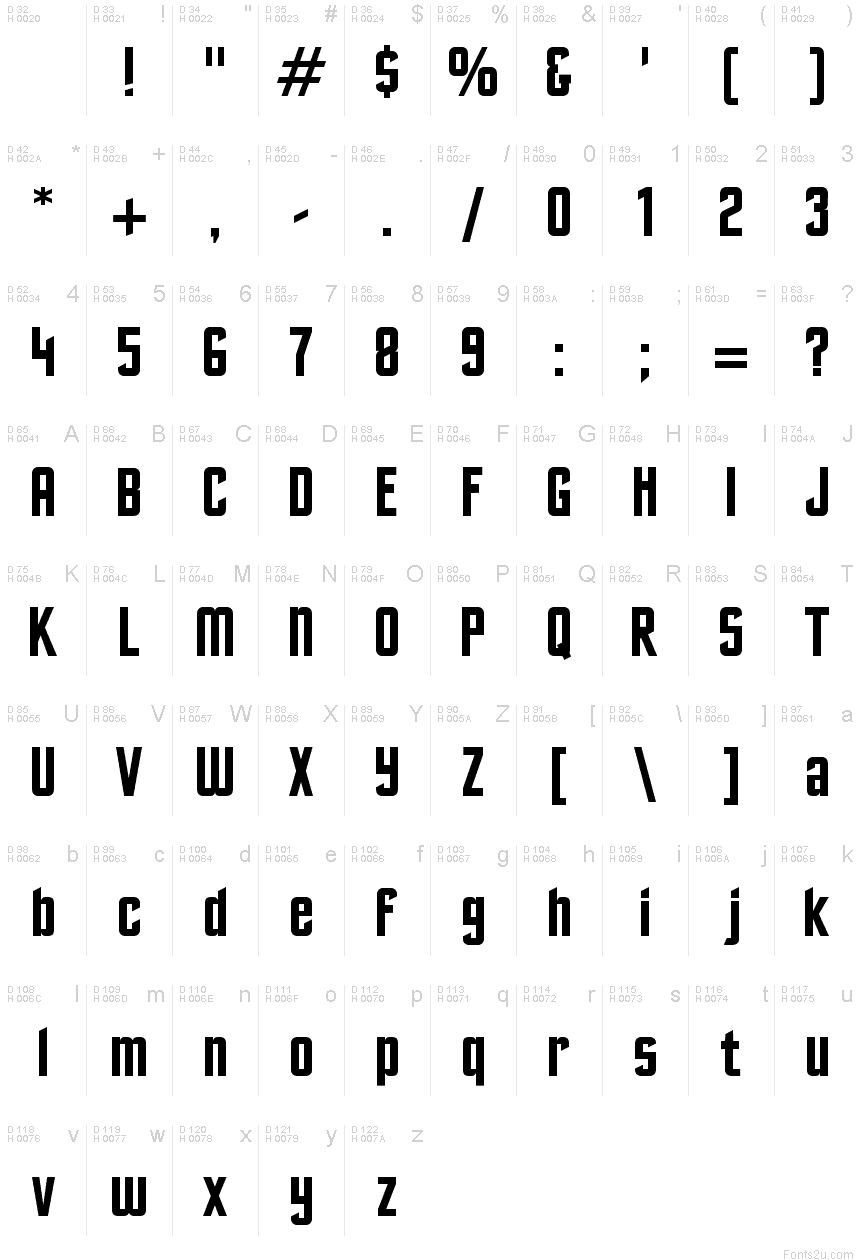
Excelsior Sans to darmowy krój typu display w techno klimacie, o ostrym, futurystycznym charakterze. Wielkie litery są wysokie, wąskie, jakby wykute z solidnych bloków, z wyrazistymi diagonalnymi cięciami i ściętymi rogami, co nadaje im mechaniczny rytm, zupełnie inny niż w przypadku neutralnych bezszeryfów.
Idealnie sprawdzi się na plakatach sci-fi, w brandingu gier, na okładkach muzycznych, w tytułach czy grafikach eventowych z branży sportowej lub technologicznej, gdzie krótkie słowa wymagają wyrazistej sylwetki. Jako darmowy font, świetnie nadaje się też do logotypów, monogramów i dużych inicjałów – jego zwarte, kanciaste formy idealnie do siebie pasują, zachowując śmiały wygląd nawet w bardzo krótkich tekstach.